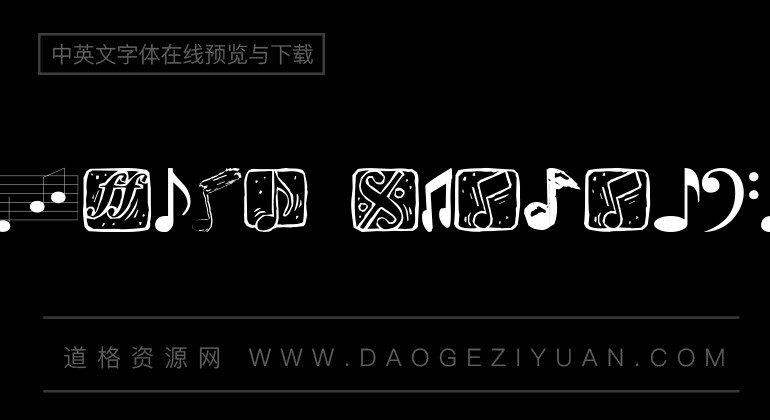
Music Elements
Music Elements 字体是一款专为音乐家而设计的字体,具有音乐符号、拍号、节拍器和乐谱等元素,可用于创作歌词、编曲、乐谱等,使音乐创作更加便捷。它的特点是字体简洁大方,适用于多种尺寸,可以让音乐创作变得更加精美。
Music Elements是一款非常不错的手写艺术字体,具有很好的视觉感,适合于文化类的宣传设计、商业类品牌的广告和产品包装设计以及个性化文字排版等较多场景。